いろんな書体のフォントがたくさんあり、見ているだけで楽しくなります。
でも、たくさんありすぎてどのフォントを使えばいいかわからなくなってしまいますよね?
なんかおしゃれな書体だから使ってるでは、伝えたいことが伝わらないことがあります。
今回は書体の向き・不向きでどのフォントを使うのが正解か考えていきましょう。
フォントの役割って?
おしゃれなフォントがたくさんありすぎて、どれを使えばいいかわからなくなることはありませんか?
ただ、闇雲に選んでも仕方がありません。
まずは、フォントが果たす役割を考えて見ましょう。
フォント自体がデザインの要素でもあり、伝える言葉でもあります。
そのため「用途にあったデザインであること」と「文章が読めて伝わること」が両立する必要があるのです。
書体の向き・不向き
01文章向きの書体
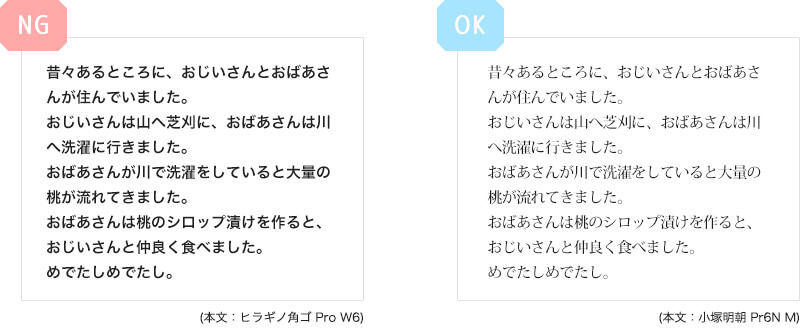
じっくりと読ませたい文章は、シンプルな書体が向いています。
太文字がぎっしり並ぶと黒々として見にくくなります。
そのため、すっきり見える細めの書体を選ぶ方がいいでしょう。
02見出し向きな書体
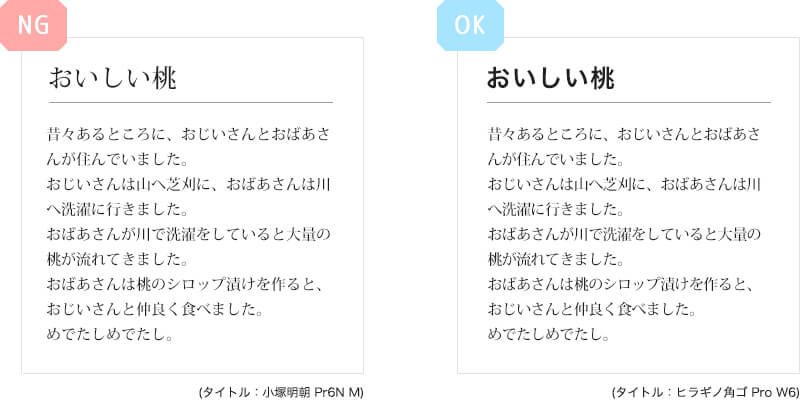
見出しは太文字を選ぶといいです。
「視認性」を高めることで、概要や全体の構造が理解できます。
03装飾向きな書体
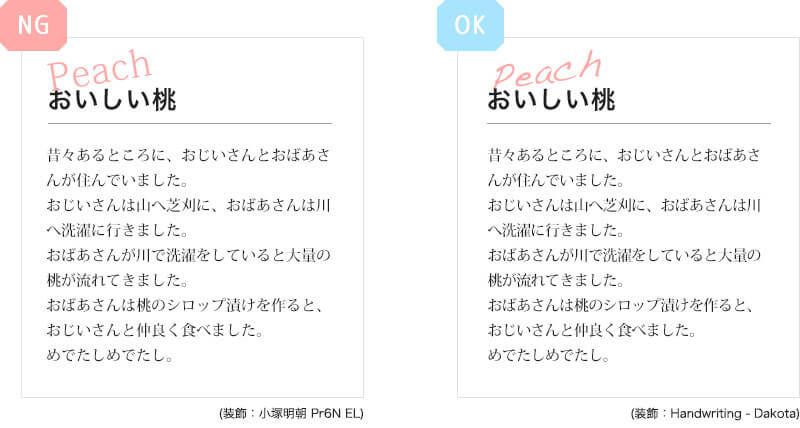
読ませるためよりも、華やかにするために、書体を使用する場合は装飾的な書体がいいです。
まとめ
いかがだったでしょうか?
今回説明したのは、あくまで基礎知識なので状況によっては当てはまらない場合もあります。
しかもフォントは選んで終わりではなく、サイズ感や文字間、行間の調整も行いながら全体バランスを取る必要があります。
やることは色々ありますが、フォントにたくさん触れることで少しずつ感覚を掴んで行くようにしましょう。